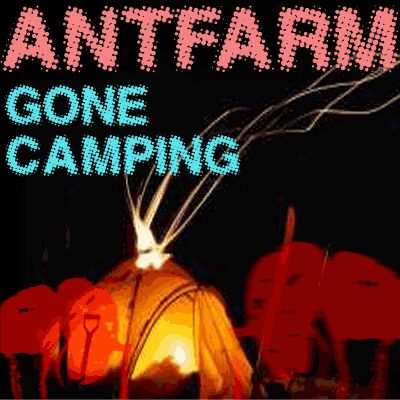
AntFarm autorstwa Klausa Nielsena to darmowy, „nadgryziony” krój pisma typu display, który wygląda, jakby został wydrążony przez rój drobnych kropek. Każda litera zbudowana jest z gęstych, atramentowych plamek, które łączą się w wyraziste kształty, nadając napisom ziarnistą, niemal wibrującą teksturę. Delikatny łuk wielkich liter dodaje dynamiki i charakteru, sprawiając, że tekst wydaje się żywy, a nie sztywny czy wygładzony.
AntFarm zapewnia surowy, namacalny styl nagłówków, który natychmiast przyciąga uwagę – idealnie sprawdzi się na plakatach koncertowych, fanzinach, tytułach horrorów czy science-fiction, okładkach eksperymentalnych albumów oraz w wyrazistym brandingu. Ten darmowy font świetnie wygląda w dużych rozmiarach, gdzie jego kropkowana struktura może „odetchnąć”; w tekście głównym zestaw go z prostym, neutralnym krojem bezszeryfowym, aby „nadgryziona” tekstura pozostała w centrum uwagi.
The polkadot camping ants from mars...